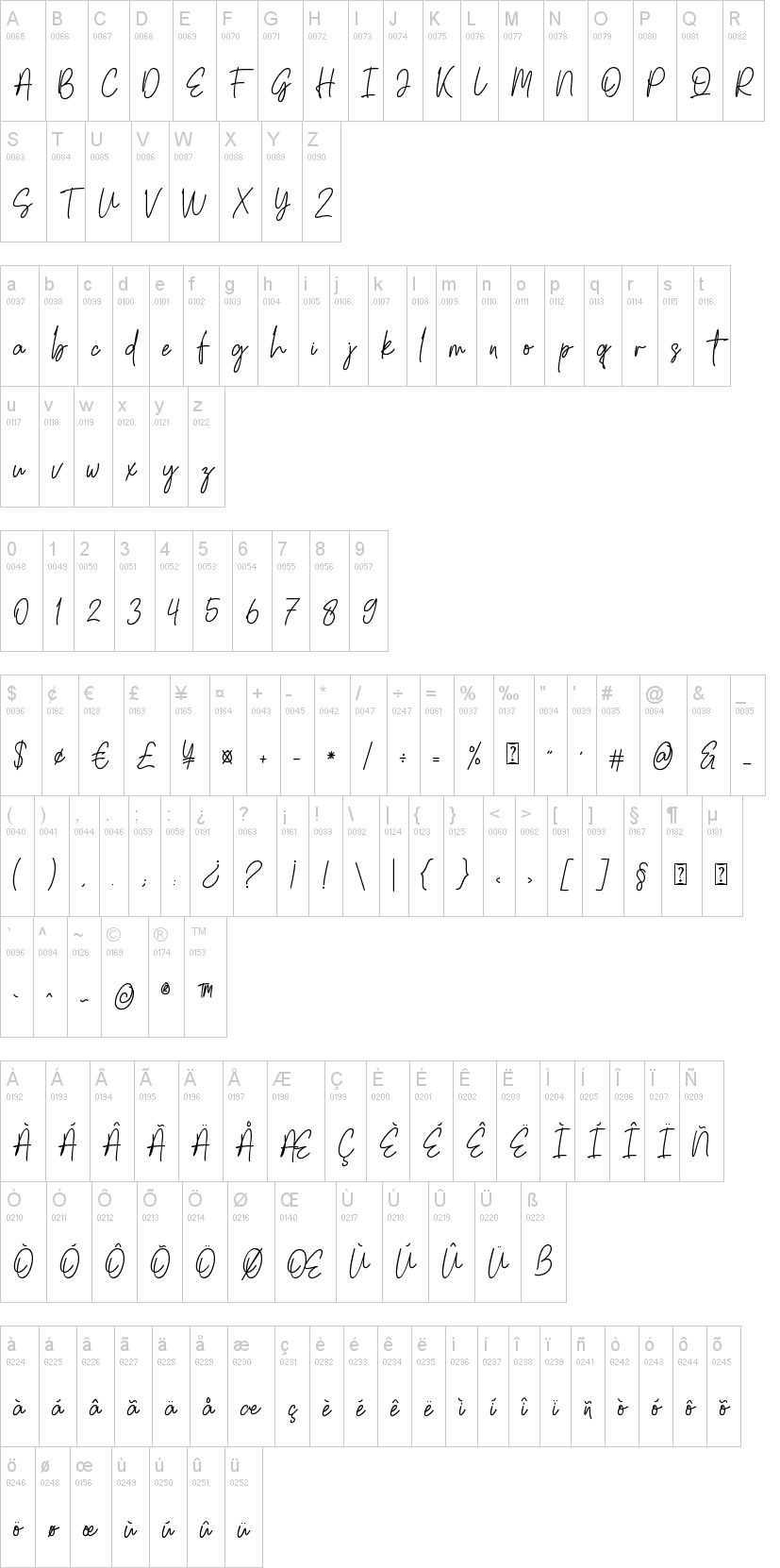
South Signature
? South Signature 是一款由南方字体设计的手写体字体,它可以帮助您在网站和印刷品上创建独特的个性化设计。它具有温暖的调调,柔和的设计,它可以让您的作品充满活力和生机。它也可以与其他字体搭配使用,以获得更强烈的视觉效果。
South Signature是一款非常不错的手写艺术字体,具有很好的视觉感,适合于文化类的宣传设计、商业类品牌的广告和产品包装设计以及个性化文字排版等较多场景。
South Signature字符映射图